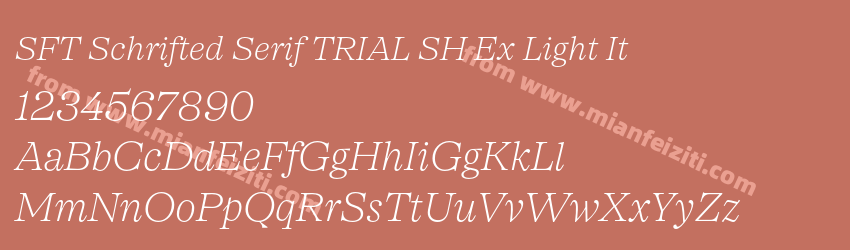
SFT Schrifted Serif TRIAL SH Ex Light It
字体名称: SFT Schrifted Serif TRIAL SH Ex Light It
本款“SFT Schrifted Serif TRIAL SH Ex Light It”是一款书写很新颖的字体,字体大方,适合各种设计作品使用!欢迎下载!